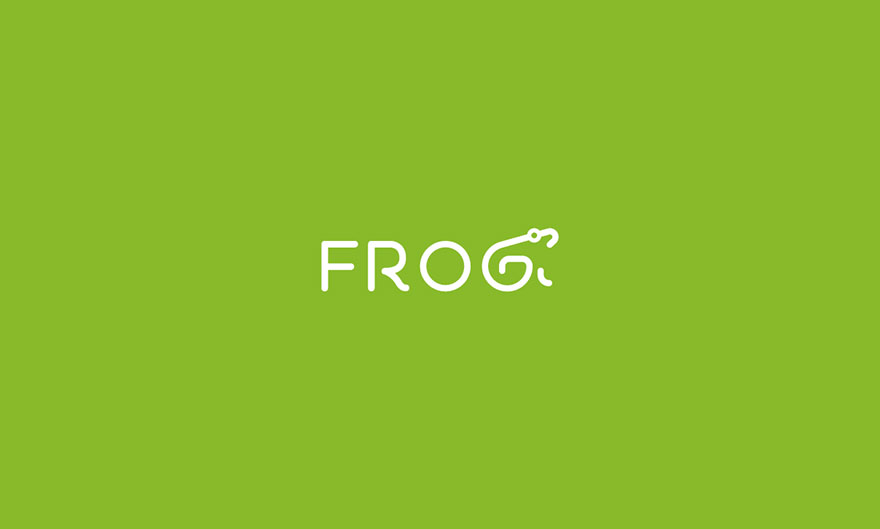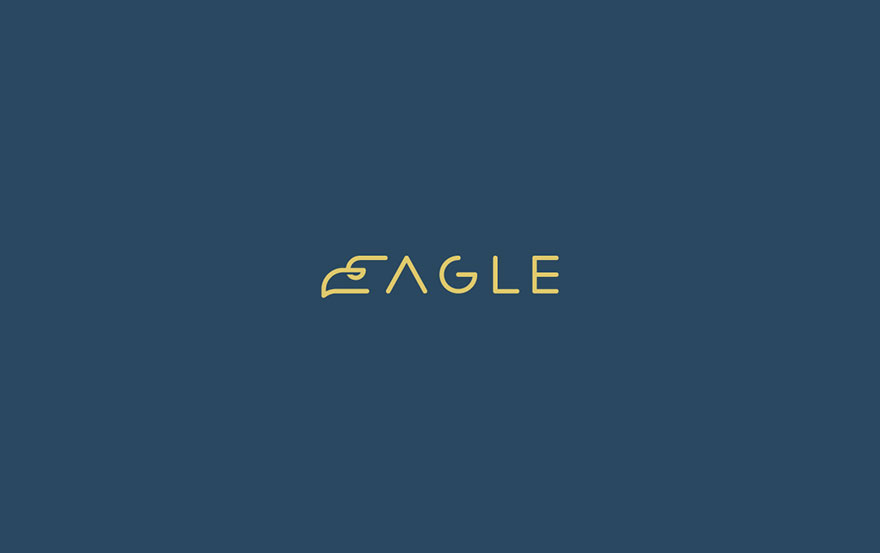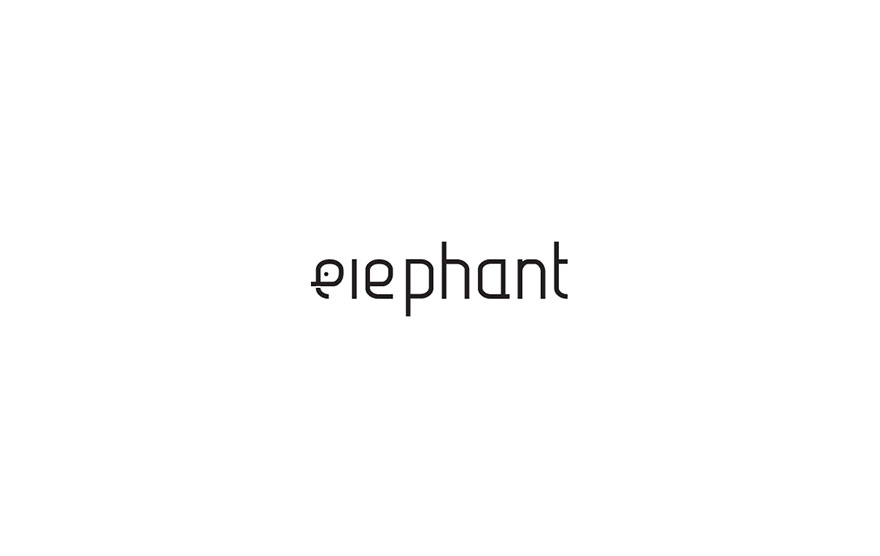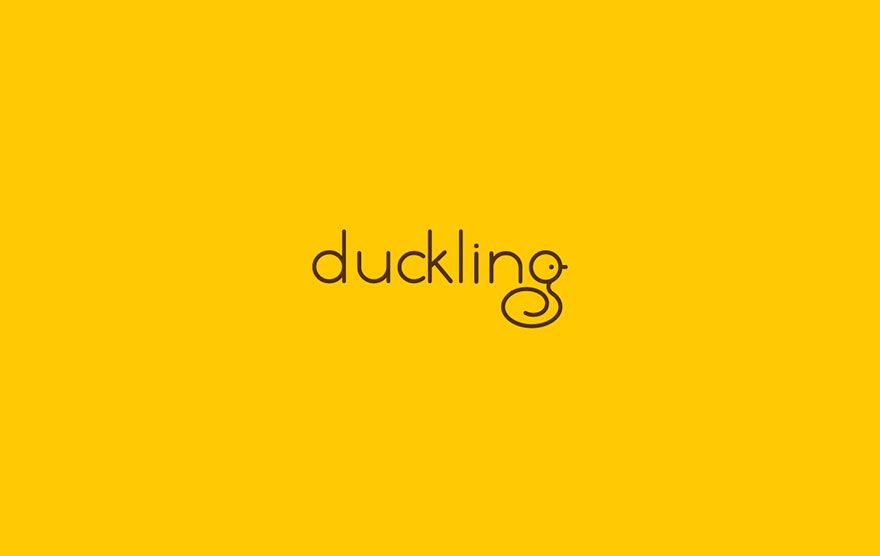
Shibu: tipografía, líneas y animales
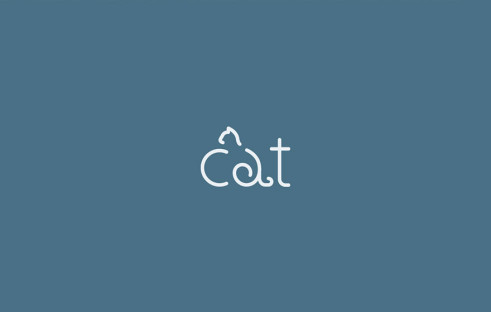
Shibu es de Kochi. Puede que la frase suene a risa, pero es así. Shibu es el nombre del diseñador gráfico freelance del que venimos a hablarte hoy en un proyecto que aúna tipografía y animales, y es de Kochi, una ciudad de la India.
Bueno, en realidad, de Shibu no vamos a contarte mucho más que eso, porque el muchacho no se prodiga mucho ni cuenta nada de sí mismo por las redes sociales y, claro, así es complicado hablar de alguien. Sin embargo, su proyecto nos ha parecido tan inspirador, que aún así nos hemos lanzado a hablar de él… Ya veremos si las palabras se nos quedan cortas. Palabras, de eso va el asunto.
Viendo su Behance, podemos intuir que lo que le va a Shibu son las marcas y la tipografía. ¡De hecho tiene una fuente gratis para descargar! ;)
En este proyecto lo une un poco todo. Se propuso crear nombres de animales en los que estuvieran incluidos esos mismos animales. Animal Wordmarks las llama él. Así consigue re-crear a la criaturita e integrarla en su nombre, sin más artificios, sólo con líneas y dos colores. ¡Y lo consigue modificando una única letra de la palabra! Este trabajo tan minimalista nos ha recordado al de los títulos de películas de Luca Costea y Eduard Cîrstea que os mostramos recientemente.
Unos juegos de creatividad que merece la pena plantearse aunque sean simplemente como trabajo personal: tú ya sabes que la creatividad no es otra cosa que un músculo que hay que entrenar todos los días. ¡No hay más secretos!